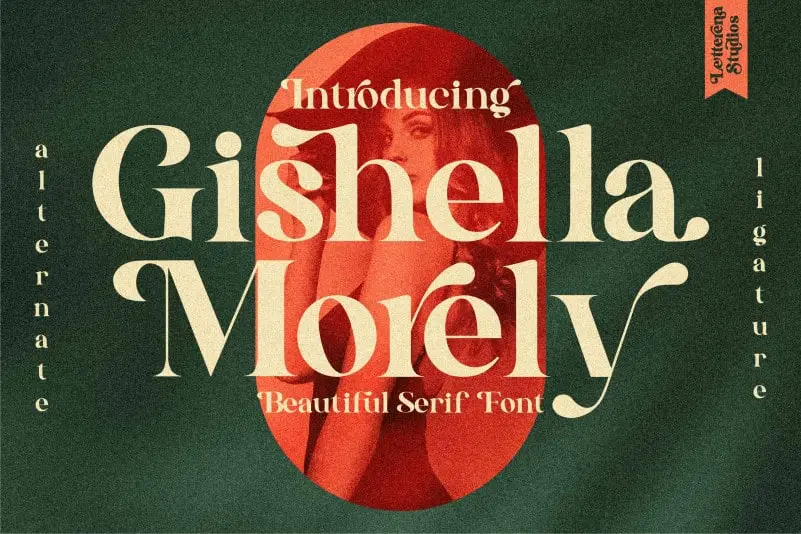
Gishella Morely Serif Font – Download Grátis
A Gishella Morely Serif Font é uma escolha incrível para quem busca um estilo sofisticado e forte. Este tipo letra serif tem uma grande versatilidade, ideal para aplicativos que vão desde cartões de agradecimento até cabeçalhos, garantindo um toque romântico para seus projetos futuros. A fonte Gishella Morely Serif é perfeita tanto para personalizar cartas e anúncios quanto para gráficos digitais e impressos, tornando-a uma opção versátil que encaixa-se em qualquer projeto. Com seu design elegante e forte, a fonte Gishella Morely Serif vai fazer toda a diferença em sua próxima produção visual.